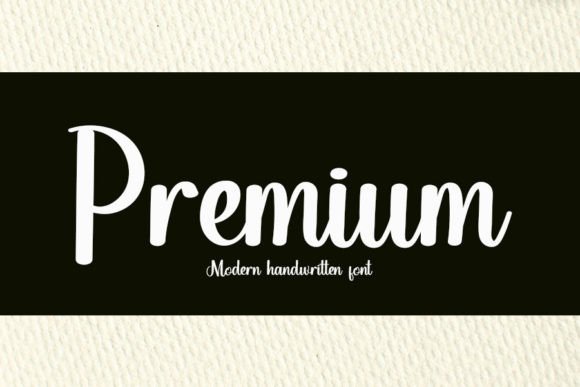
Premium
Premiumのような高品質の素材をお探しの場合、このプレミアムパッケージはクリエイティブなプロジェクトに素晴らしい選択です。
精密に作られたPremiumは、クリーンなベクター、滑らかなタイポグラフィ、そして安心のための商用ライセンスを提供します。
POD(オンデマンド印刷)製品、結婚式の招待状、またはソーシャルメディアのグラフィックを作成している場合でも、Premiumは理想的です。